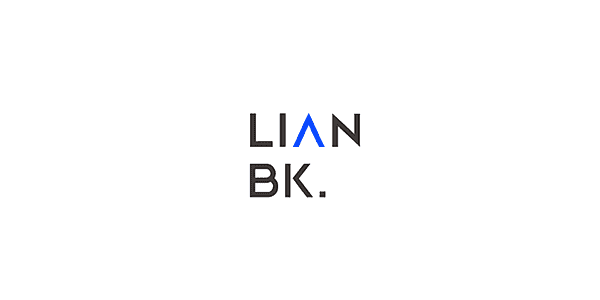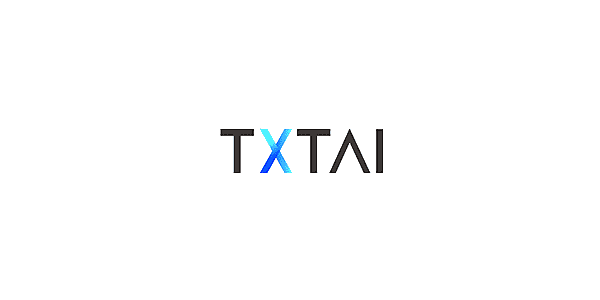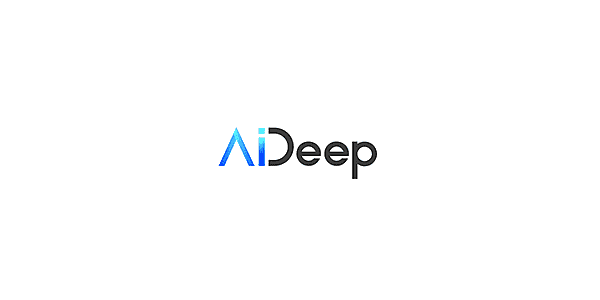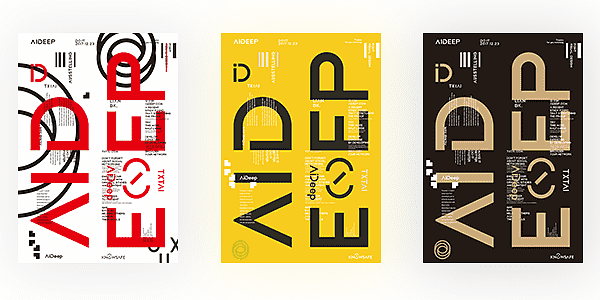
团队今年定位国际化,将大部分业务都定位为英文命名,所以考虑了品牌VI的标准化,为了方便,所以做了一整套字体,方便日后新业务出现还在为了各种LOGO设计而费脑筋,设计者为网络尖刀UED团队,小伙子。
中文字体做了700多个,实在做不动了,所以先发了26个英文大写+26个英文小写,额外0-9这10个阿拉伯数字。
“Ai Deep Bold”是一款书写很新颖的字体,字体大方,适合各种设计作品使用!欢迎下载!